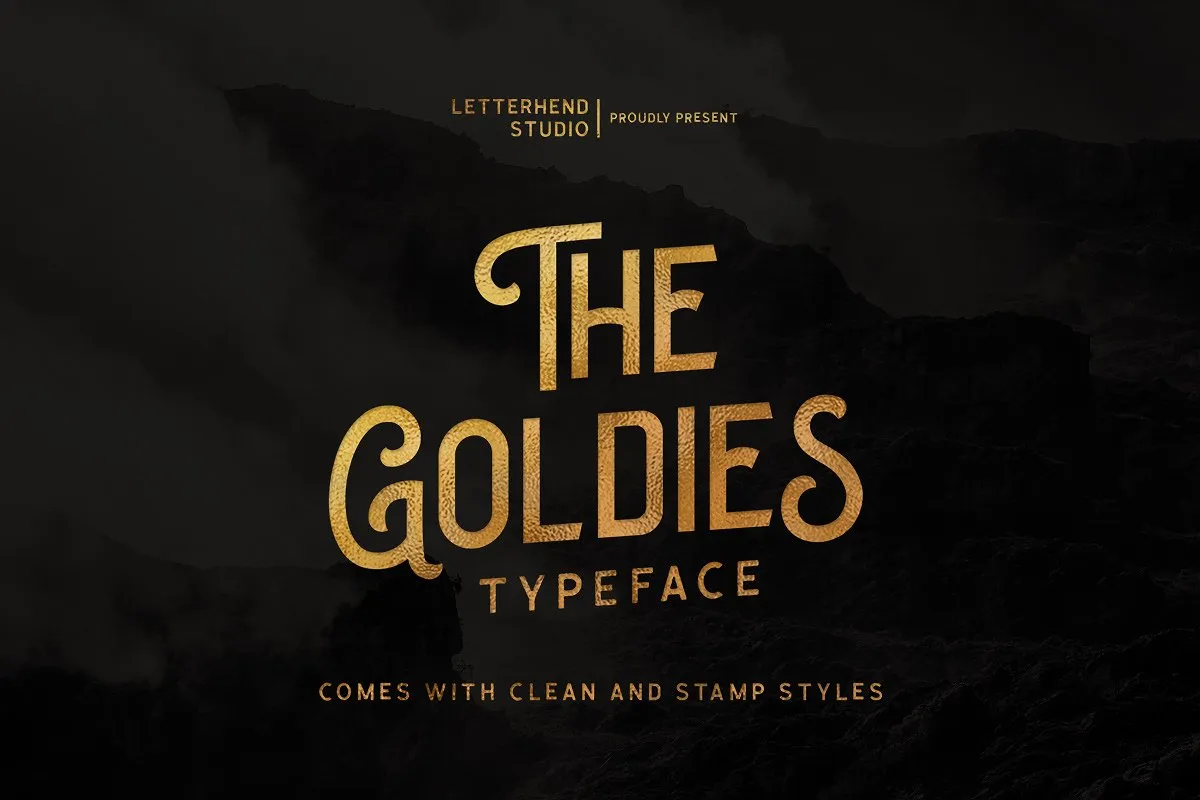
A font The Goldies Display Font é uma elegante escolha para qualquer projeto visual que exige estilo forte e personalidade, seja no design de logotipos, embalagens ou materiais promocionais. Perfeita para headlines e outros textos destacados por sua disposição poderosa e detalhes ricos, The Goldies é uma fonte de família criada especialmente para aquelas necessidades específicas. Ela vem em versões maiúsculas e minúsculas, símbolos e números, alternativas estilizadas, ligações e outros elementos essenciais para qualquer projeto que deseje se destacar. Ideal tanto para designers gráficos quanto para quem busca uma fonte moderna e atraente para aplicar em camisas de moda ou cartões de convite personalizados. The Goldies é um atalho perfeito para aqueles projetos onde o design deve falar por si só, criando um impacto imediato que destaca o seu trabalho.